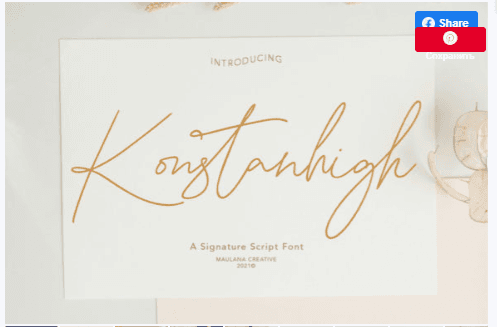
Konstanhigh Font
Konstanhigh - это модный и элегантный шрифт с тонкими буквами. Этот шрифт аккуратно обработан и очень детализирован. Какой бы ни была тема, этот шрифт станет прекрасным дополнением к вашей библиотеке шрифтов, поскольку он может улучшить любое творение.